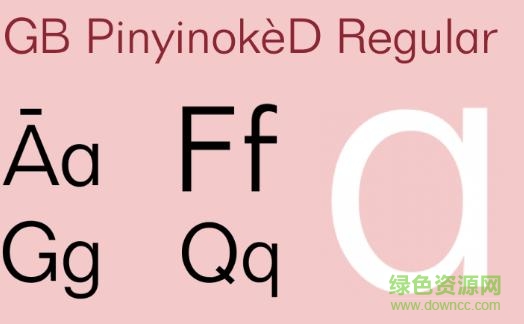
gb pinyinok-d字體是一款獨(dú)特的漢語(yǔ)拼音字體,每一個(gè)數(shù)字按鍵都代表著不同的音標(biāo),常常用于出版印刷領(lǐng)域,大家在本站下載安裝后即可輸入使用,歡迎下載!
1.以詞為拼寫單位,并適當(dāng)考慮語(yǔ)音、語(yǔ)義等因素,同時(shí)考慮詞形長(zhǎng)短適度。
2.基本采取按語(yǔ)法詞類分節(jié)敘述。
3.規(guī)則條目盡可能詳簡(jiǎn)適中,便于掌握應(yīng)用。